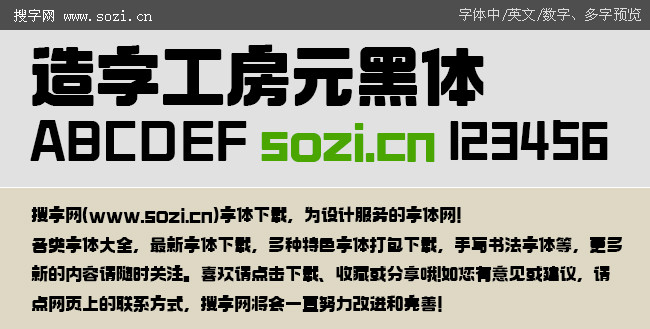
造字工房元黑體
搜字網(wǎng)給大家提供一款造字工房元黑體中文字體下載,造字工房元黑體字體結(jié)構(gòu)嚴(yán)謹(jǐn)、字形端正、筆畫(huà)橫平豎直,字形風(fēng)格中正剛肅,筆畫(huà)首尾巧用圓角,令其在古樸沉厚的同時(shí)又不失和柔儒雅之風(fēng)。適合應(yīng)用于書(shū)籍裝幀設(shè)計(jì)、包裝設(shè)計(jì)、海報(bào)設(shè)計(jì)、網(wǎng)頁(yè)設(shè)計(jì)等應(yīng)用。(本字體為個(gè)人非商用版,如需要商用請(qǐng)聯(lián)系官方購(gòu)買(mǎi)版權(quán))